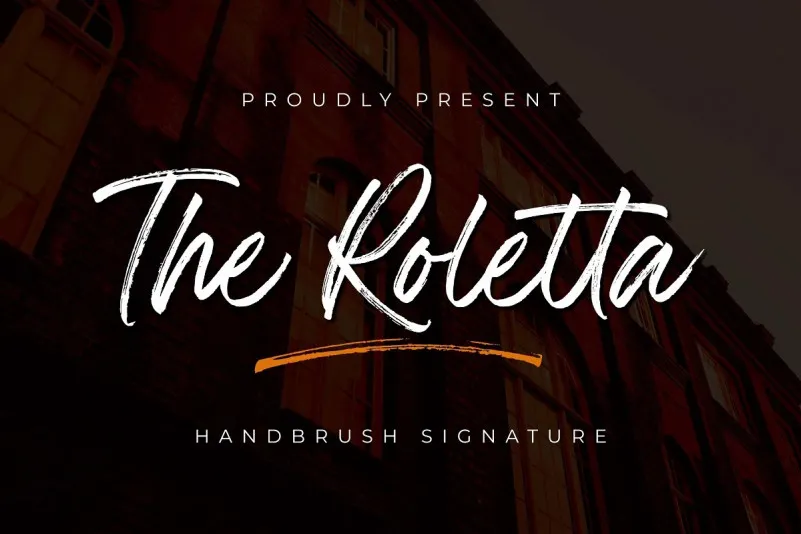
The Roletta Font
A fonte The Rolleta é uma criação artesanal do designer Almarkha Type, apresentando linhas texturizadas que dão ao tipo uma aparência quase retrátil e multifacetada. Ela é baseada na escrita de um marcador seco, onde as letras são criadas com esferas sobre papel e depois scaneadas e desenhadas meticulosamente em formato vetorial. Esta característica torna The Rolleta única, oferecendo uma aparência encantadora e autêntica que combina elementos relaxantes e descontraídos ao texto. O que torna a The Rolleta ainda mais especial é o seu design com quatro estilos principais: regular, inclinada, alternativa e inclinada alternativa. Estes estilos proporcionam um olhar mais natural em sua fonte, adaptando-se facilmente para uma variedade de aplicações, como designs de móveis de casa, campanhas de marca, logotipos, marcas de produto ou até mesmo como o fundo em fotografia e marcadores d’água. É perfeitamente adequada para um amplo espectro de projetos gráficos, desde a criação de materiais de decoração até as aplicações mais discretas, como marcações digitais. Sem dúvida, The Rolleta é uma opção ideal para quem busca uma fonte com aparência autêntica e natural que se destaca em qualquer projeto visual.